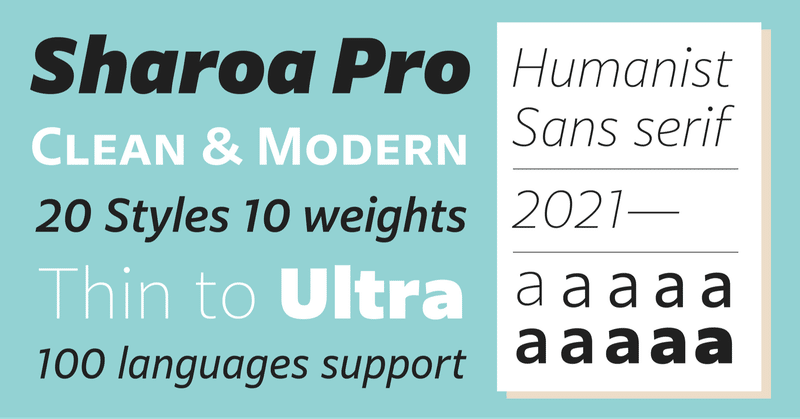
シンプルで温かみのある表情のヒューマニストサンセリフ「Sharoa Pro」【2021年新書体】
今回は、2021年10月21日にリリースが迫る新書体から欧文書体「Sharoa Pro」をピックアップします。
欧文はどれも同じに見える、どの書体を選んだらいいのかわからない…という方も多いかもしれませんが、欧文書体の基礎知識をはさみつつご紹介していきますのでご安心を…!
これまで欧文の設計をじっくり見る機会がなかったという方も、きっと見え方が変わるはずです(フォント沼のもう一層深い部分の存在に気づきます)。
デザイナーインタビューでは、Sharoa Pro開発秘話や欧文書体制作の奥深さも語っています。
1.ウエイト展開豊富な本文向け欧文書体
・コンセプト
Sharoa Proはシンプルですっきりとした印象の本文向けサンセリフ体です。
「あおとゴシック」の従属欧文のベースのデザインにもなっており、クリーンな印象の和文に合わせたコンセプトで開発されました。
欧文書体のジャンル、ご存知のものはありますか?
欧文の分類で最もメジャーなものとしては、セリフ体とサンセリフ体があります。
“ セリフ ” と呼ばれる飾りのついたセリフ体に対して、“ サンセリフ ” とはフランス語で「飾りのない」を意味します。
和文書体で例えると、セリフ体が明朝体にあたるのに対し、あおとゴシックとの混植を目的に作られたSharoa Proは飾りのないサンセリフ体、和文のゴシック体にあたります。
・ファミリー展開
Sharoa Proはあおとゴシックの従属欧文のデザインのベースにもなっていますが、こちらではさらにずらっと…ウエイトが多いです!
UltraLightからUltraまでの10ウエイト展開で、それぞれイタリックを含めた20書体と幅広いファミリー展開になっています。
本文利用を主な用途としているためよく使われるRを中心に、ウエイトに応じてキャプションや見出しサイズでの利用に適した設計になっています。
本文組みのイメージがこちらです!
ローマン体(正体)と比較して、ややカリグラフィックにデザインされたイタリック体は、長文組版に適度なリズムを与えることができます。
・文字セット
書体名にもついている「Pro」は文字セットを表しており、こちらはモリサワの独自セットです。
モリサワの欧文の文字セットはProとPEの2種類あり、英語などで使われるラテン文字以外にもダイアクリティカルマーク付き文字などを搭載し多数の言語に対応しており、Proは100言語、PEは151言語をカバーしています。
また、どちらも本格的な文章組版をサポートする数字や記号のバリエーションなど、代替字形を豊富に搭載しています。
2.シンプルなヒューマニストサンセリフ
・スタイル
サンセリフ体のスタイルはグロテスク、ネオグオテスク、ジオメトリック、ヒューマニストの4つに分類され、Sharoa Proは「ヒューマニストサンセリフ」にあたります。
ヒューマニストサンセリフは、他のスタイルに比べて手書きの風合いの残る骨格で温かみのある表情が特徴です。
Sharoa Proの “ スッキリとした ” 印象は、グロテスクの “ 無骨な印象 ” と対比すると分かりやすいかもしれません。
…サンセリフ体の特徴、つかめてきたでしょうか?
Sharoa Proはやや広めのカウンター(文字の中に含まれる空間)で、明快なエレメントは親しみやすい印象の読みやすい書体になっています。
また、字幅とスペーシングは比較的広めに取ることで、長文でも読みやすくなっています。
3.デザイナーインタビュー
ここまで欧文基礎と一緒にSharoa Proの特徴をご紹介してきましたが、さらにデザイナーからSharoa Proの制作秘話や欧文書体の見極め方を語ってもらいました。
ーSharoa Proはどんなコンセプトで開発が始まったのでしょうか?
樽野:あおとゴシックとの併記利用を目的とした欧文書体を作るという企画だったので、コンセプトはある程度和文に合わせてシンプルでスッキリとした印象の書体を目指しました。 モリサワのライブラリにもスタンダードに使える本文向けのサンセリフ体があったらいいなと思い、ウエイト展開の充実した欧文単体でもリリースすることになりました。
ー欧文書体の選び方がわからない、という声をよく聞くのですが、Sharoa Proはどんなところで使ってもらいたい書体ですか?
樽野:難しいですね…書籍や公共の場など情報を正確に伝えたい場面で使ってもらえるといいな、と思いつつも、自由に使ってほしいのでデザイナーからは使用場面を限定するようなことはあまり言いたくないんです(笑)シーンを選ばずに使ってもらえると思います!
たしかに、欧文書体の選び方は難しいですよね。前提として、フォントは色々な目的で開発されているので、文字セットやOpenType機能などデザインの前に使いたい条件に合っているかは大事なポイントです。
それをクリアした上で言うと、Sharoa Proはシンプルながら温かみもある書体なので、きっちり情報を伝えたいけど、無機質に、事務的にはしたくない場面とかが合うのかなと思いました。
ー欧文書体の雰囲気を掴むのが難しいのですが、Sharoa Proの “ 温かみ ” や “ 手書きっぽい ” といった特徴は具体的にはどんなところに現れていますか?
樽野:ヒューマニストサンセリフというジャンルが “ 温かみ ” や “ スッキリ ” といった特徴を持っていて、具体的には手書きに近いストロークが取り入れられていることが挙げられます。例えば、「アパーチャー(開口部の開き具合)」が開いているという特徴によって明るい印象の文章組になります。
一方で、Sharoaはヒューマニストの中では手書きっぽさを抑えたストロークを採用しています。 “ 手書きっぽさ ” という特徴によって癖のある書体に見えないように、あまり目立つような特異性のある骨格は避けるようにしました。イタリックに関してはローマンよりはもう少し手書きっぽい形を強くしています。
ーなるほど。手書きっぽさのあるスタイルの中で、その具合を調整しているんですね。
樽野さんはここ数年欧文書体をメインに担当されてましたが、Sharoa Proの制作で難しいところはありましたか?
樽野:これまでもベージックなものが多かったため、特徴をなくしていくというのは基本的には作りやすかったですかね。でも、特徴を出そうと思って出たわけではない私自身の癖は自分ではわかりにくいので、そこをいかにコントロールするのかというのはすごく難しかったです。特に、ディレクターからは数字が結構個性的だと言われました。これまでに制作した書体の影響で自分ではシンプルな形のつもりでも曲線に癖が出ているみたいで、中でも数字が一番指摘されましたね…。
あとは、特徴的な形は取り入れない方針で進めていたのですが、つい遊び心を持たせたくなってしまって小文字のzを少し独特なものにしてみたら却下されてしまいました…。もちろん、本文書体の範疇でちょっと色を出すような遊び心だったのですが、目につく個性を少なくするというコンセプトだったので今回はダメでしたね(笑)最終的には全体を見て揃っていたので特異な形は避けておいてよかったと思っています!
ーあおとゴシックとの整合性はどのように取っていったのですか?
樽野:試作段階の和文と欧文でモックアップを作るなどしてデザインの整合性をある程度とってから制作を進めました。文字数が少ないこともあって欧文が和文より先行して完成したのですが、最後にあおとゴシックにデザインを合わせるという再調整も必要なくスムーズに制作が進められたのはよかったです。
一方で、あおとゴシックに合わせながら欧文としても使いやすいウエイトを設定していくのは少し難しかったですね。欧文のファミリーとしては細かいウエイトの刻み方なのですが、和文の太さに合わせることを前提にするとどうしてもウエイト数が多くなってしまいます。単純に欧文のみを作ろうと思ったらまた違ったウエイトの構成になっていたかもしれないですね。とはいえ、ウエイト数が多いことはデメリットではなく、細かい太さの調整をしたい誌面などでは使いやすいんじゃないかと思います。
ー日本人のデザイナーとして、欧文書体制作で難しいと感じることはありますか?
樽野:作成時は実際に文章を組んでチェックや調整をするのですが、ダイアクリティカルマーク(発音区別符号)付きの文字など馴染みの無いものはネイティブではないので “ 読む ” という感覚が難しいですね。日本語の濁点だったら読んだ時に大きすぎるとか、文字として認識しづらいなどの感覚がありますが、マークの大きさや位置などは実際に読めるわけではないのでそういった判断が難しく、日々勉強ですね。
ー逆に和文制作と欧文制作で通ずる点はどんなところがありますか?
樽野:一つは文字の機能的な面で、当たり前ですがどんな言語でも「誰かが情報を読むためのもの」という使用目的は変わらないというところです。どんなところに使われるか、どんな情報にその書体が必要とされるのかなどを考えることも書体制作では大事で、その点では和文と欧文どちらも原則は変わらないなと気づきました。プロセスは違うんですけど、機能的な目的が一緒なのでチェックするべきポイントとかやることは分かってくるかなと思います。
デザイン面では、アウトラインを作るときにそれぞれの文字の成り立ちに深く関わってきた道具を意識するということです。日本だったら筆など、それぞれの文字を書くときに使われていた道具が現代の文字の形にも影響していると思います。そこはやっぱり日本人だから欧文でその感覚が掴みづらいことはありますが、逆にいうと道具をちょっと意識することでその言語の文字のデザインを理解するのに役立つので、すごく大事なことだなというのを両方経験して感じるようになったと思います。
ー和文書体と欧文書体、どちらを制作する上でもそもそもの文字としての使用目的やルーツとなる道具を意識することが大切なんですね。
Sharoa Pro、どんな書体かお分かりいただけましたでしょうか?
和文書体に比べてとっつきにくく感じる方も多いと思いますが、樽野さんのおっしゃる通りSharoa Proはシーンを選ばずに使いやすい欧文書体なので覚えておいて損なしです!